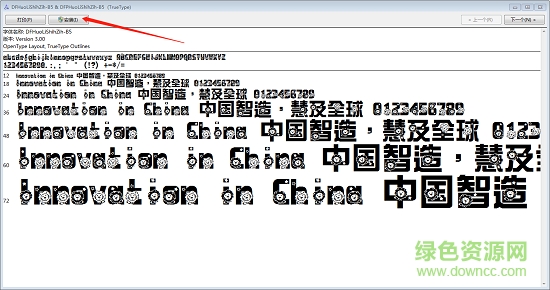
華康活力獅子體是一款由華康字體打造的一款非常有趣的動(dòng)物字體,字體中插入了超多可愛的獅子頭像,帶給用戶一種非??蓯鄣募纫暩?,喜歡就來綠色資源網(wǎng)下載吧!
華康活力獅子體字體是華康字體推薦的一款字體。它的辨識(shí)度很強(qiáng),基本一眼就知道這是活力獅子體,因?yàn)樵僖矝]有一款字體是獅子頭為主的了;另外,這款字體在英文、漢字以及數(shù)字上有會(huì)有效獅子頭哦!
一款讓你感受到獅子可愛一面的字體
華康活力獅子體活力四色,可以用來做手機(jī)主題字體
超強(qiáng)辨識(shí)度的字體,適用于卡片以及給類特色設(shè)計(jì)